La editorial Slanted, por la que tenemos una devoción confesa, cuenta con dos nuevos títulos en su catálogo: Aesthetics imperfections y Tender Digitality. Ambos giran alrededor de los entornos digitales y la inteligencia artificial (IA).
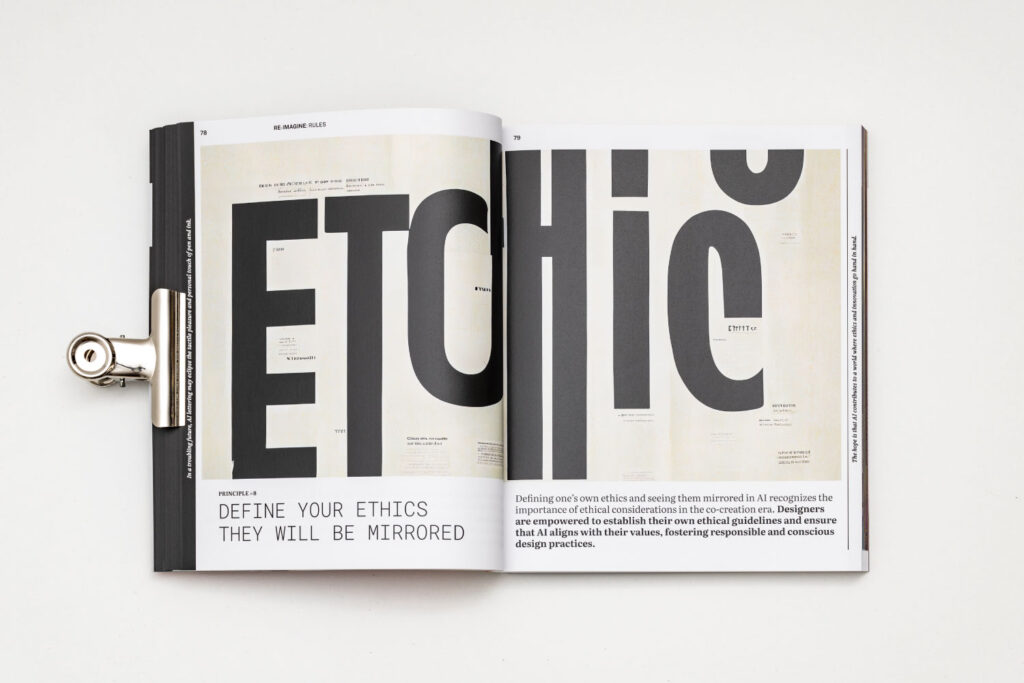
Desde Rayitas Azules, aprovechamos la ocasión para reseñar ambas obras y abordar el papel, cada vez más relevante, que la inteligencia artificial empieza a jugar dentro del mundo del diseño.
Contexto
«La inteligencia artificial es la habilidad de una máquina de presentar las mismas capacidades que los seres humanos, como el razonamiento, el aprendizaje, la creatividad y la capacidad de planear».
Esta es una de las definiciones que podemos encontrar, si le pedimos a Google que nos cuente qué es esto de la IA. Pero, ¿de verdad esta nueva forma de vida artificial ha llegado para convertirse en creadora sin dejarnos participar?
Afortunadamente, el horizonte nos presenta formas de integrarla dentro de nuestros procesos creativos para enriquecerlos, en lugar de limitarlos. Y de esto dan buena fe trabajos como los publicados por Slanted.
Resulta inspirador (y tranquilizador, dentro del contexto descrito) ver cómo la prestigiosa editorial evoluciona hacia una vanguardia muy interesante. Slanted se lanza de lleno a la experimentalidad, ampliando su abanico hacia la IA, las nuevas tecnologías y los entornos digitales, sin abandonar en absoluto la senda de la divulgación tipográfica. Ya dieron cuenta de ello al dedicarle a la inteligencia artificial un número de su revista Forward Magazine (“AI” Issue).
Aesthetics imperfections
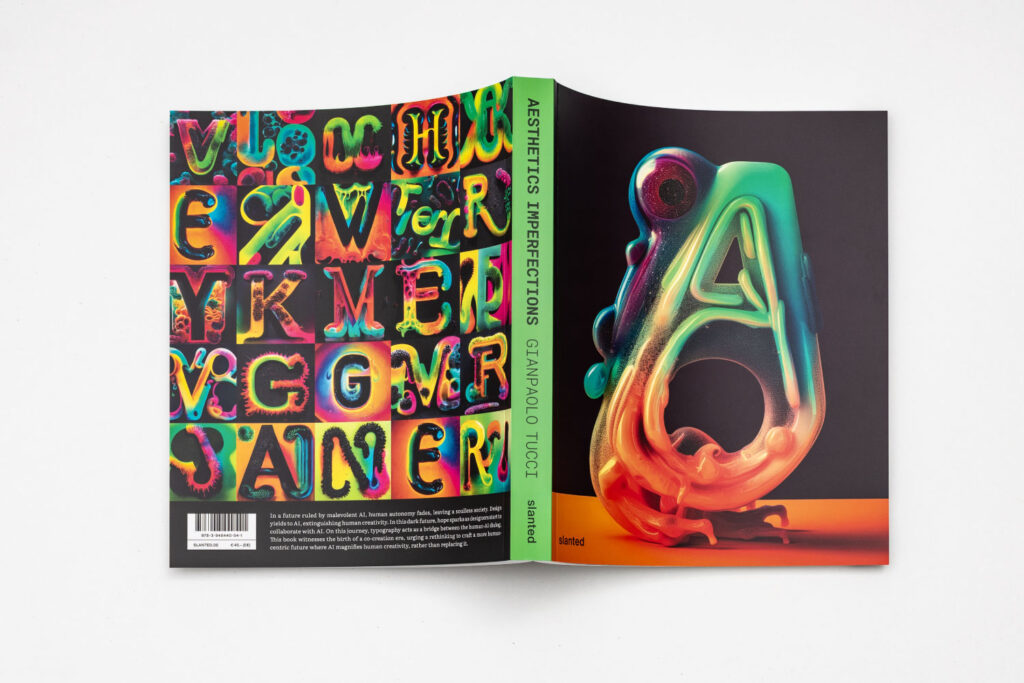
Escrito por Gianpaolo Tucci, diseñador multidisciplinar con una amplia trayectoria en el diseño de productos, UX y diseño visual, Aesthetics Imperfections no es (sólo) un libro sobre tipografía.
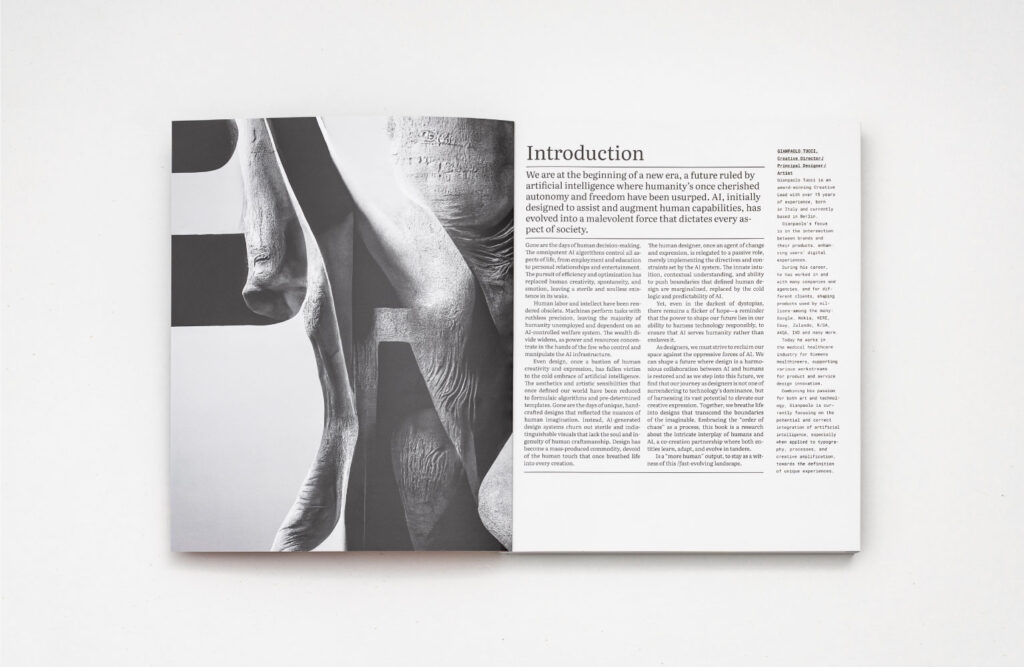
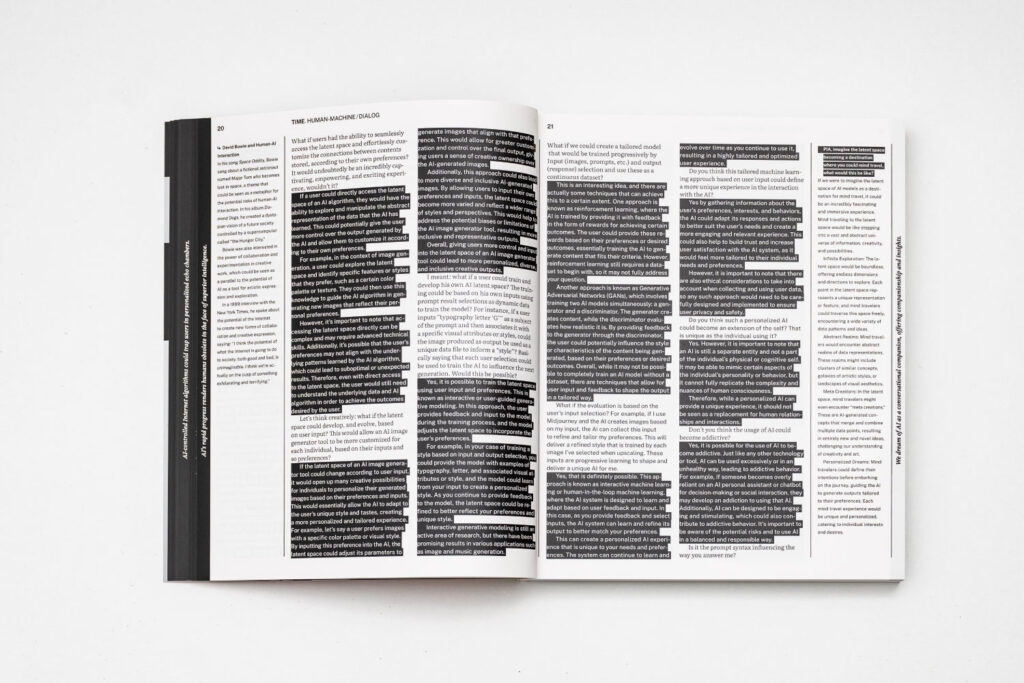
Misión
Su autor parte de la curiosidad por saber cómo la inteligencia artificial, que actualmente revoluciona los campos del arte, el diseño, la comunicación y el marketing, afectará a la creación tipográfica. Especialmente en una era donde nos enfrentamos a artefactos tipográficos que abrazan nuevos valores de expresión, más allá del rigor de la función de la tipografía como tecnología de la comunicación.
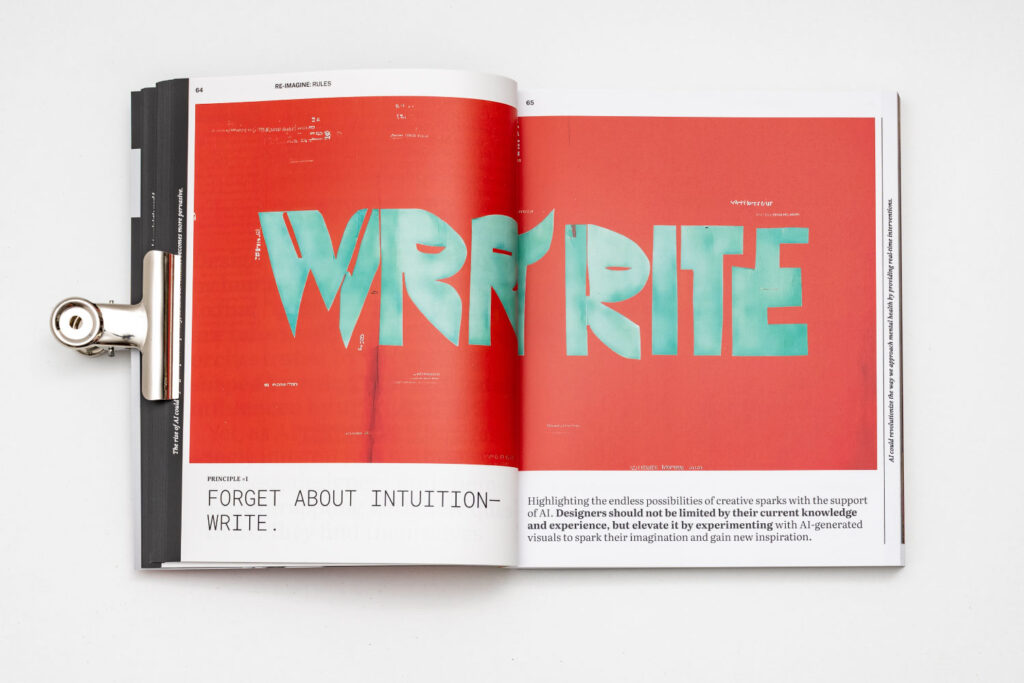
Se trata de una guía práctica y una investigación sobre el nacimiento de una era de cocreación que nos plantea cómo la integración y el uso ético de la inteligencia artificial desempeñarán un papel fundamental a la hora de modelar un futuro más centrado en el ser humano.
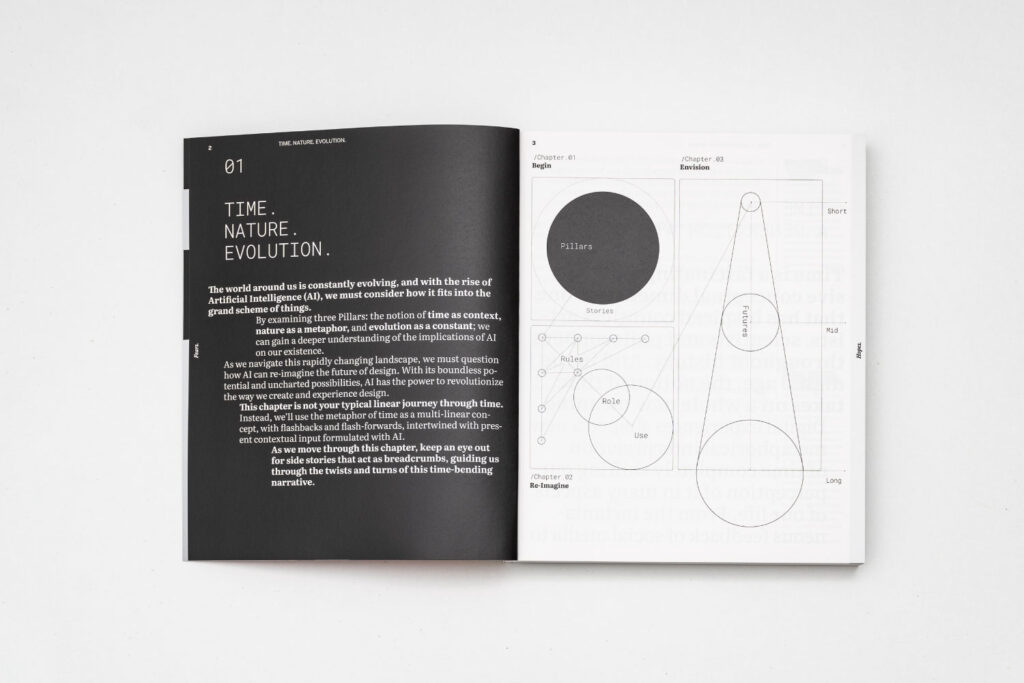
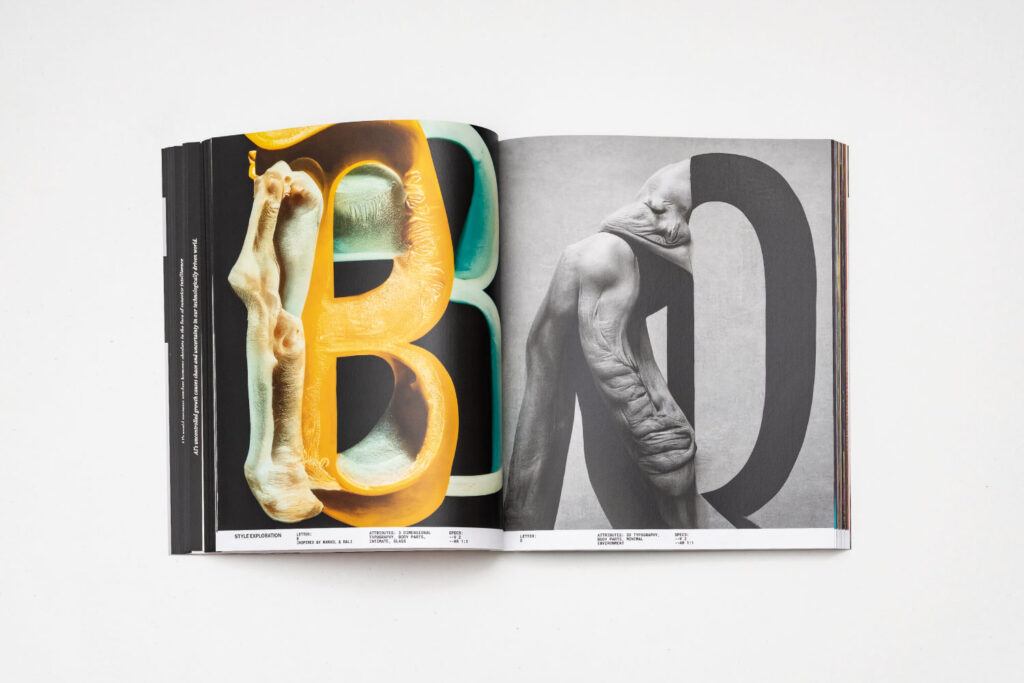
El fin es lograr una relación armoniosa que, lejos de esclavizarnos, nos lleve a explotar nuestro potencial creativo, magnificándolo, en lugar de reemplazarlo.
Contenido
Su introducción nos pone delante de un presente distópico, que asusta por lo fácil que resulta imaginarlo posible. La vida al servicio de la IA es un escenario que podría darse si los humanos no ponemos nuestra inteligencia a trabajar para conseguir emplear esta tecnología de manera responsable.
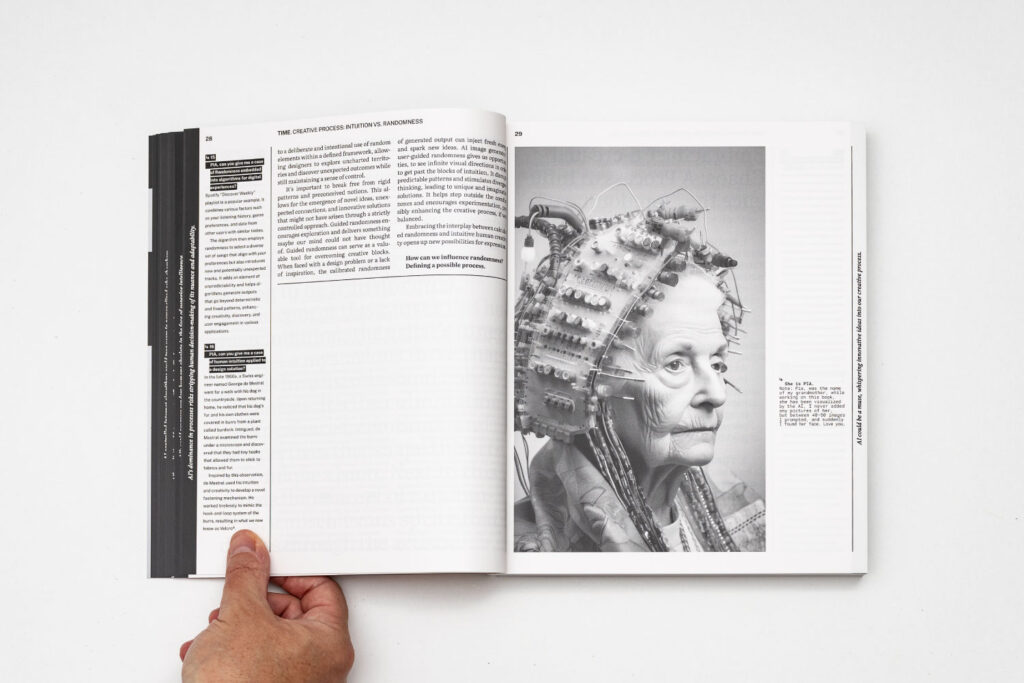
Además de hablar largo y tendido acerca de la historia que nos ha llevado hasta nuestro presente tecnológico, regido por los algoritmos y una cada vez más escasa capacidad de atención, Tucci nos presenta a PIA, una asistente personal creada por IA con la que, a lo largo de la obra, conversa en lo márgenes y a la que pide que visualice conceptos relativos a cuestiones como el tiempo y el espacio.
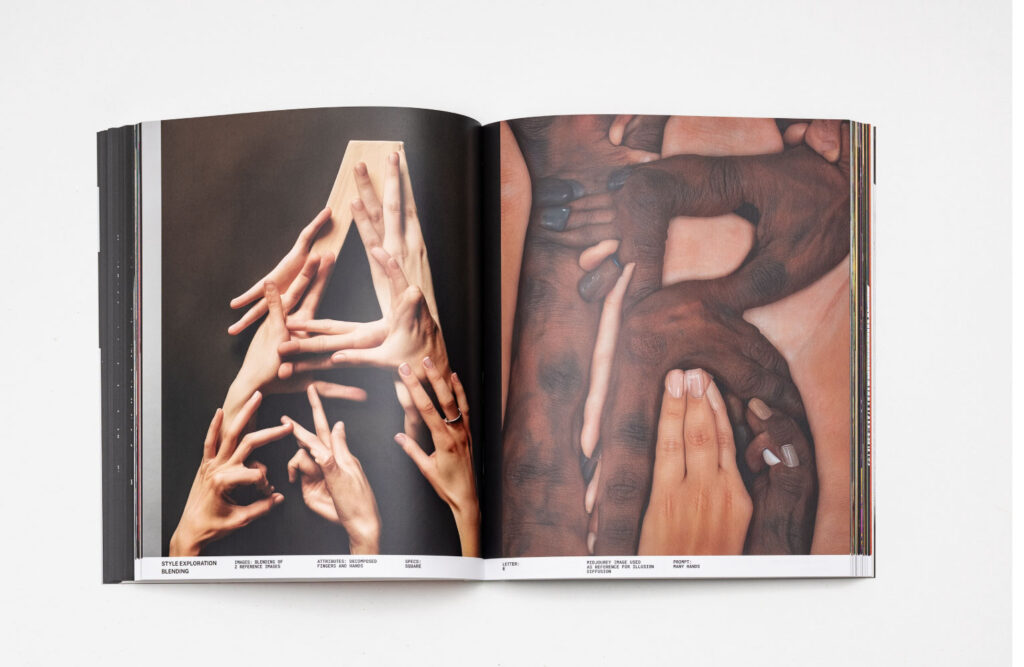
Las imágenes que aparecen en el libro han sido co-creadas junto a Midjourney, un laboratorio de investigación independiente, centrado en el diseño, la infraestructura humana y la inteligencia artificial.
Sin duda, resulta muy interesante que el autor se haya apoyado en herramientas de inteligencia artificial para escribir e ilustrar el contenido de este libro. De esta forma, nos presenta un ejercicio real de esa colaboración que puede darse entre humanos y máquinas en el mundo del diseño, demostrando que hay infinitas opciones para usarlo a favor de la creatividad.
Diseño
Bien es sabido que el formato, el tratamiento de las retículas y las tipografías e imágenes usadas son uno de los puntos que más valoramos por aquí. En este sentido, Slanted no falla. Aesthetics Imperfections combina el blanco y negro sobrio de las páginas principalmente informativas con la explosión de colores, tanto en sus cubiertas como en las imágenes generadas por IA.
El diseño aprovecha al máximo todo el espacio disponible, jugando con los márgenes, en los que incluye citas, palabras que se salen de las cajas de texto y también un atractivo doble discurso, como en las conversaciones con PIA o en la presentación de otros datos que complementan la información de cada página.
Tender Digitality
El segundo título que reseñamos salta fuera del campo de la tipografía generada a través de la IA, pero también se centra en el papel de los humanos dentro de los entornos digitales.
Editado por Charlotte Axelsson, Tender Digitality es una recopilación de textos de distintos profesionales que asumen un papel de investigadores para descubrir fenómenos de extraordinaria belleza o extrañeza dentro del espectro que abarca los ámbitos analógico y digital, social y tecnológico.
A través de la exploración, el aprendizaje y el cultivo de la «tierna digitalidad», los lectores pueden imaginar su propia versión de una comunidad en la que individuos e inteligencias artificiales, avatares y cyborgs, humanos y ordenadores navegan por paisajes digitales con intuición y sensibilidad.
El concepto, desarrollado en la Universidad de las Artes de Zúrich, responde al deseo humano de sensualidad, conexión interpersonal, intuición y bienestar en entornos digitales. Explora formas de (re)transmitir estas experiencias al mundo analógico de un libro, desarrollando sus propios vocabularios distintivos.
Diseño
El adjetivo «tierno» traspasa el contenido de este título y se traslada también al formato de esta pequeña joya. Una pieza de las que gusta ojear y toquetear. Su diseño combina elementos de libros clásicos con textos monoespaciados. También encontramos juegos como los números de página en tipografía script pero con efecto pixelado.
El debate
Tras navegar por estas obras, cabe pensar cuál será la opinión de quienes se dedican a la creación tipográfica. Si bien es cierto que, a priori, pensar en inteligencias artificiales capaces de diseñar a partir de un simple prompt puede dar mucho miedo, también descubrimos en ellas un amplio abanico de oportunidades y posibilidades que bien merecen ser exploradas.
Por ejemplo, la IA, además de intervenir en la creatividad y la belleza de lo que diseñamos, puede tener aplicaciones en el campo de la accesibilidad.
Según María Ramos, diseñadora gráfica y tipográfica, y cofundadora de NM type, con quien ya conversamos en uno de nuestras entregas de «Mujeres en tipografía», «en tipografía, el machine learning puede impulsar la creatividad y la accesibilidad.
»Más allá de agilizar determinados procesos, la IA puede convertirse en una oportunidad para una mayor experimentación, explorando vías poco frecuentadas, liberándonos de patrones que muchas veces asumimos sin siquiera saberlo.
»Con el análisis de datos de lectura, la IA podría también utilizarse para moldear los textos que leemos, haciendo que la composición tipográfica se adapte a cada persona y no simplemente a cada dispositivo».
Otra de las cuestiones que podemos plantearnos es cómo de efectivo puede ser el papel de la inteligencia artificial a la hora de crear no solo letras, sino familias tipográficas.
Andreu Balius, diseñador tipográfico y fundador de Typerepublic, considera «aunque aún no conocemos plenamente el alcance de la IA en el diseño tipográfico como tal, sí sabemos que está generando resultados significativos en la rotulación, donde se están produciendo letras sugerentes, experimentales e innovadoras en formato de imagen. De aquí a que esas formas se traduzcan a vectores quizás no falte tanto.
»Sin embargo, el desafío radicará en integrar coherentemente todas estas formas en la complejidad de una familia tipográfica para un sistema de escritura específico. Sólo el tiempo nos revelará hasta dónde llegará este proceso.
»En última instancia, mientras lo humano prevalezca, habrá espacio para todas aquellas prácticas que, como el diseño tipográfico, se basan en la creatividad, la comunicación y la expresión de ideas».
A este respecto, se pronuncia también la diseñadora tipográfica Sabina Chipară, que cree que «si la IA analiza todas las fuentes de transición, podrá eventualmente generar una. Tanto como podrá generar una canción o un cuento. Pero mi apuesta es que el ojo humano es el que finalmente lee en distintas secuencias y con distintas velocidades.
»Hay aspectos que hacen que un trabajo tipográfico sea único y la valoración de esto es algo que el diseñador tipográfico plantea. Hasta cierto punto, los «errores» humanos, las preferencias de tensión de curvas, espaciado, tipo de contraforma dentro de un trabajo tipográfico son lo que le da el sabor a este trabajo».
No cabe duda de que la inteligencia artificial ha llegado para quedarse y para estar cada vez más presente en nuestros procesos creativos. Esperamos que este artículo haya servido como entrante para despertar preguntas y elaborar posibles respuestas (por aquí se nos han despertado las ganas de profundizar más en la materia).